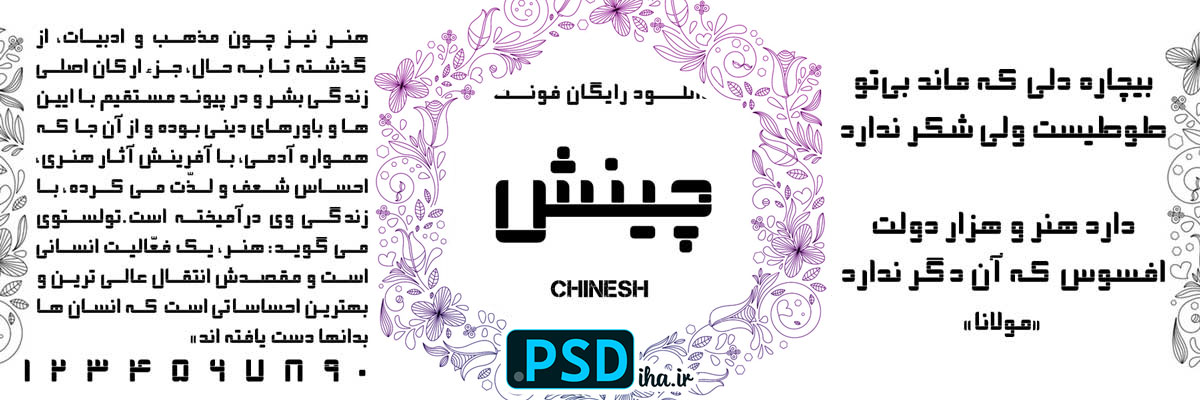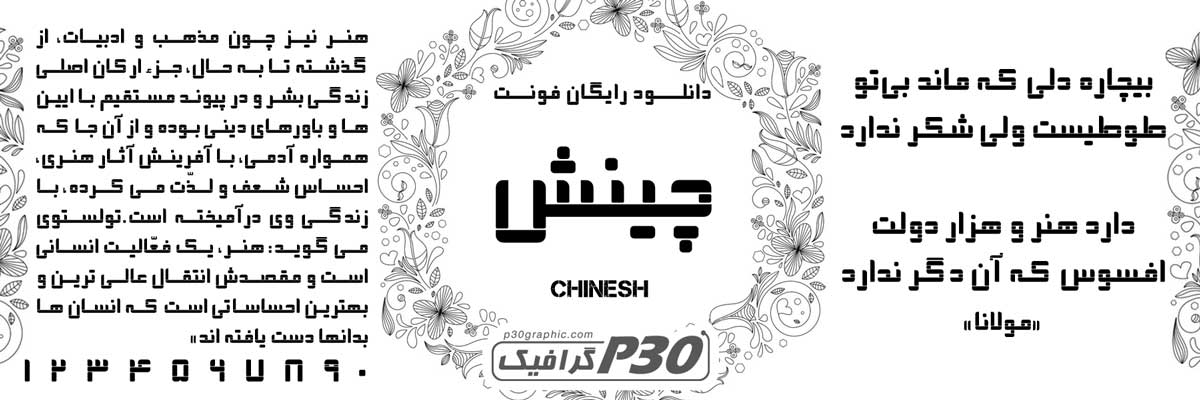
دانلود فونت چینش رایگان
دانلود فونت چینش
دانلود فونت چینش رایگان – نظم و خوانایی در هر ستون
اگه از طراحانی هستید که مرتب با اینفوگرافیک، داشبوردهای مدیریتی، گزارش‌های سالانه یا مجلات چندستونه کار می‌کنید، حتماً می‌دانید که «فاصله گذاری استاندارد» چقدر در خوانایی متن تأثیر دارد. فونت چینش دقیقاً با همین هدف طراحی شده: حروف منظم، ارتفاع یکسان و کرسی‌بندی ثابت که چشم را خسته نمی‌کند. این فونت برای پروژه‌هایی مثل کاتالوگ محصولات یا جداول آماری ایده‌آل است.
من خودم در طراحی قالب‌های اختصاصی برای کسب‌وکارهای خدماتی، چینش را جایگزین فونت‌های قدیمی کردم. نتیجه؟ مشتریان می‌گویند متن حرفه‌ای‌تر و به‌روزتر دیده می‌شود. اگر به دنبال فونت‌های دیگر با همین حس مدرن هستید، سری به آرشیو کامل فونت‌های سایت بزنید.